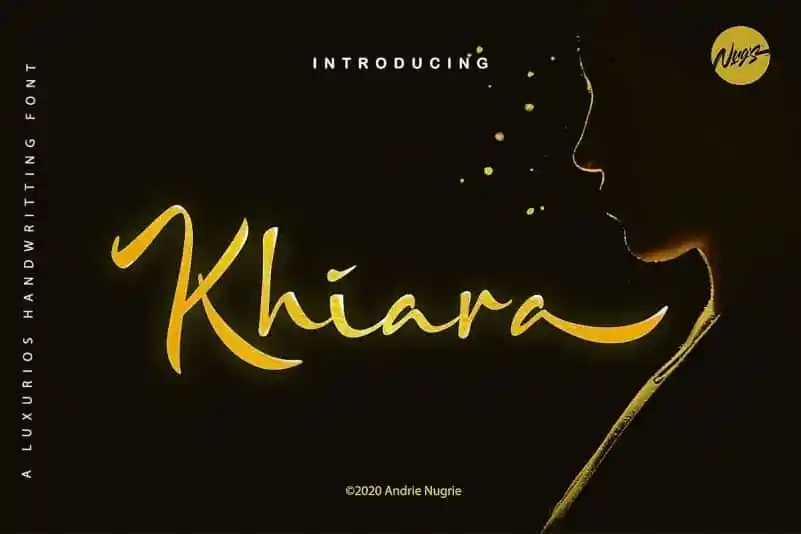
Khiara Script Font – Fonte Grátis
Khiara Script Font
A Khiara Script Font é uma elegante fonte à mão livre ideal para projetos de identidade corporativa sofisticada ou logotipos. Esta fonte foi criada pela Nug’s Project, e seu design fluido é tão profissional quanto atraente. Com mais de 430 caracteres disponíveis, ela é perfeita para manuseios em editoriais, cartões de visita, cartas pessoais, embalagens de produtos, citações escritas à mão ou qualquer outra ocasião que exija um touch de luxo e sofisticação. A Khiara Script Font oferece acesso a todos os caracteres gerais e alternativas através da PUA (Propriedade Universal), tornando-a simplesmente uma escolha perfeita para designers e criativos desejosos de personalizar seus projetos digitais.